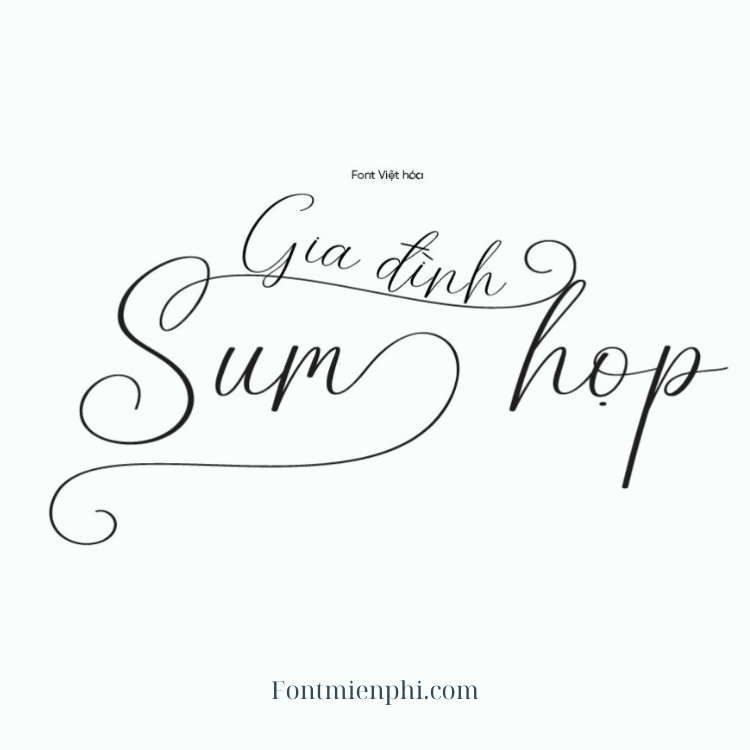
Tải Ngay Bộ Font Việt hóa Summerfun VIP Đầy Sáng Tạo Cho Học Sinh
Chào mừng các bạn đến với thế giới thiết kế đầy màu sắc dành cho môi trường giáo dục. Trong các dự án học đường, việc lựa chọn một Font Miễn Phí nhưng vẫn đảm bảo tính thẩm mỹ và dễ đọc luôn là ưu tiên hàng đầu. Hôm nay, chúng tôi xin giới thiệu bộ Font Việt hóa Summerfun VIP, một lựa chọn hoàn hảo để làm mới các bài giảng, bảng tin và tập san trường học.
Đặc điểm nổi bật của Font Việt hóa Summerfun VIP
Bộ chữ này mang phong cách viết tay hiện đại, nét chữ thanh mảnh nhưng vẫn giữ được độ dày vừa phải để tạo điểm nhấn. Font Việt hóa Summerfun VIP được thiết kế dựa trên cảm hứng về những kỳ nghỉ hè sôi động, mang lại cảm giác năng động và tràn đầy năng lượng tích cực cho người xem.
Tính ứng dụng cao trong thiết kế giáo dục
Nhờ vào sự mềm mại và thân thiện, bộ font này rất phù hợp để thiết kế bìa sách, nhãn vở hoặc các slide thuyết trình sinh động. Giáo viên có thể sử dụng để trình bày giáo án điện tử, giúp học sinh cảm thấy hứng thú hơn với bài học. Các bạn học sinh cũng dễ dàng dùng font chữ này để trang trí báo tường hoặc làm thiệp tặng thầy cô, bạn bè vào những dịp đặc biệt.
Cách tối ưu hóa Font Việt hóa Summerfun VIP khi sử dụng
Để đạt hiệu quả thị giác tốt nhất, bạn nên kết hợp font chữ này với các tông màu sáng như xanh lá, vàng hoặc cam. Điều này giúp tôn vinh tinh thần “Summerfun” mà bộ font hướng tới. Ngoài ra, việc sử dụng các ký tự đặc biệt được Việt hóa trọn bộ sẽ giúp văn bản của bạn chuyên nghiệp hơn, tránh lỗi hiển thị dấu tiếng Việt thường gặp ở các bộ font ngoại nhập.
Kết luận về bộ font chữ độc đáo